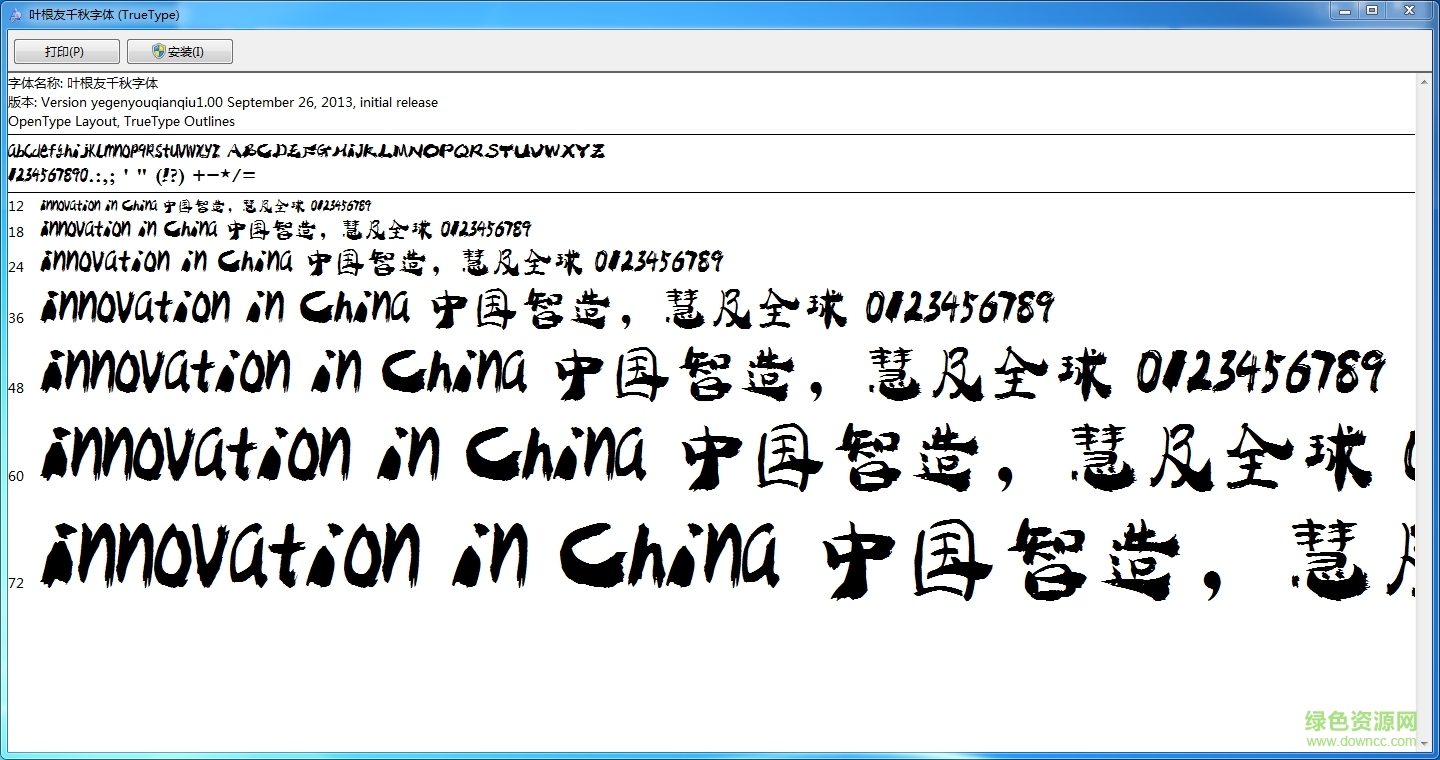
葉根友千秋字體
葉根友千秋字體是葉根由友先生寫的一款應(yīng)用于設(shè)計方面的中文簡體漢字,字體字形風格獨特,飄逸大方,整體效果十分出色,能夠適用于注冊商標、廣告設(shè)計、名片設(shè)計、包裝印刷、產(chǎn)品設(shè)計等應(yīng)用,喜歡的小伙伴快來綠色資源網(wǎng)下載吧!